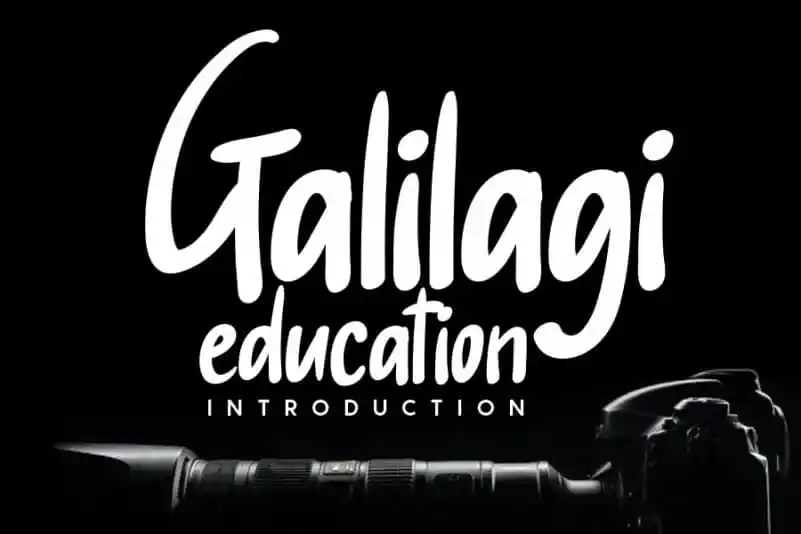
Galilagi Handwritten Font – Fonte Grátis
Galilagi Handwritten Font
A Galilagi Handwritten Font é uma elegante escolha para aqueles que buscam um acabamento único e alegre em suas criações digitais. Desenhada com ajuda de um pincel, essa fonte escrita à mão captura o espírito natural e único que é característico do estilo humano, fazendo-a perfeitamente adequada para uma ampla gama de projetos. A única limitação é a imaginação pessoal dos designers. Com sua aparência fluida e suave, Galilagi Handwritten Font será um acréscimo brilhante à coleção de seu design, complementando arquiteturas de texto de uma maneira que os leva ao próximo nível. Seja para gráficos, ilustrações ou textos, essa fonte oferece uma maneira perfeita de expressar sua personalidade e criar um visual único e agradável em seus projetos digitais.